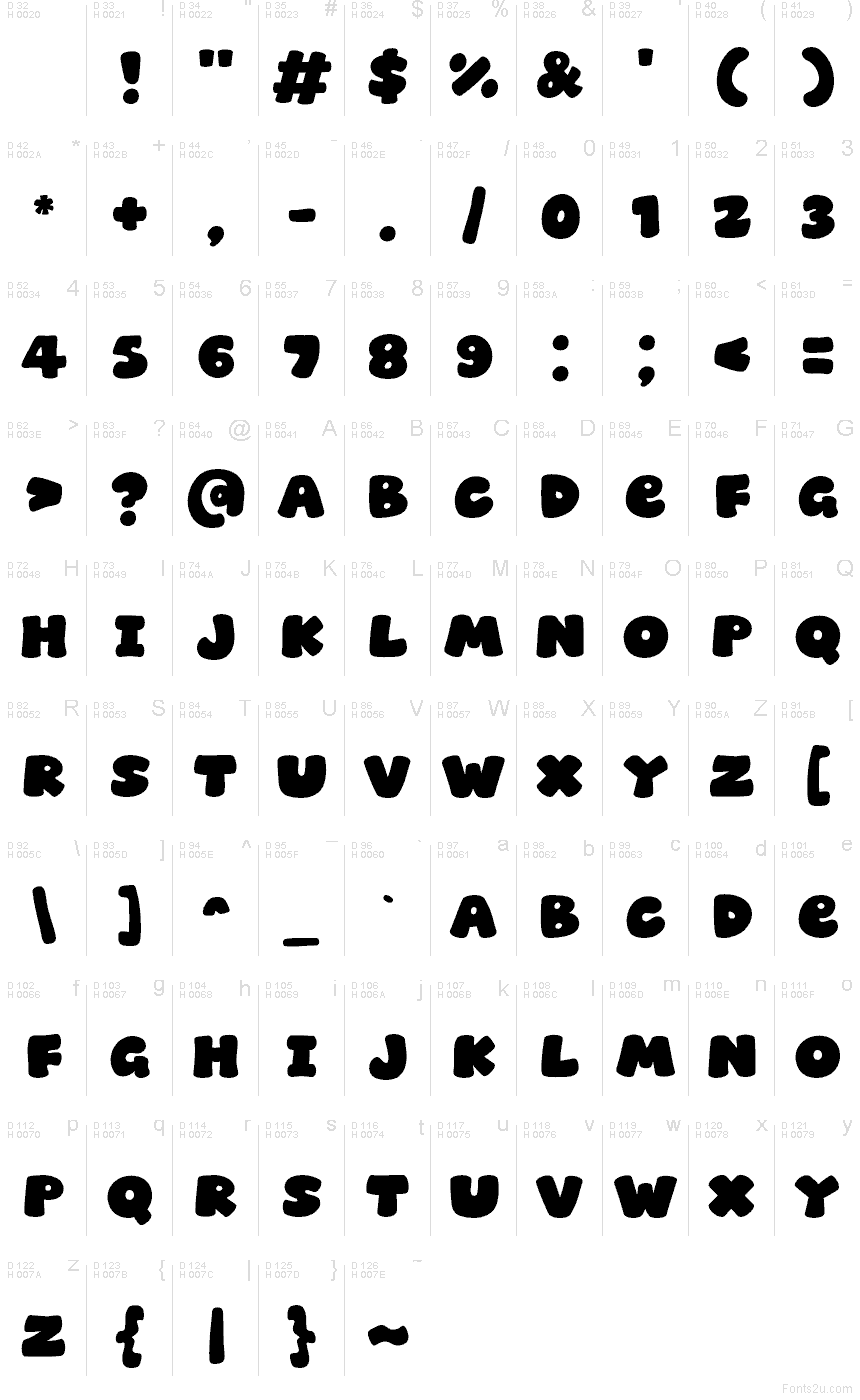
Sweet Bread od MJType je bezplatné kreslené display písmo s jemnými, obláčikovými tvarmi, ktoré pôsobí ako stvorené pre hravý branding. Písmená sú výrazné a zaoblené s mierne nepravidelnými, ručne tvarovanými proporciami, vďaka čomu sa toto písmo nachádza niekde medzi bublinovým písmom a priateľským komiksovým titulkom.
Prirodzene zapadne na logá pekární, obaly pre deti, etikety na pochutiny, pozvánky na párty či veselé príspevky na sociálne siete, kde potrebujete bezplatné písmo s výrazným a prístupným charakterom. Použite ho na krátke nadpisy, titulky v štýle nálepiek alebo obálky, keďže tieto robustné krivky a kompaktné tvary dodávajú krátkym slovám živý a trochu bláznivý nádych.